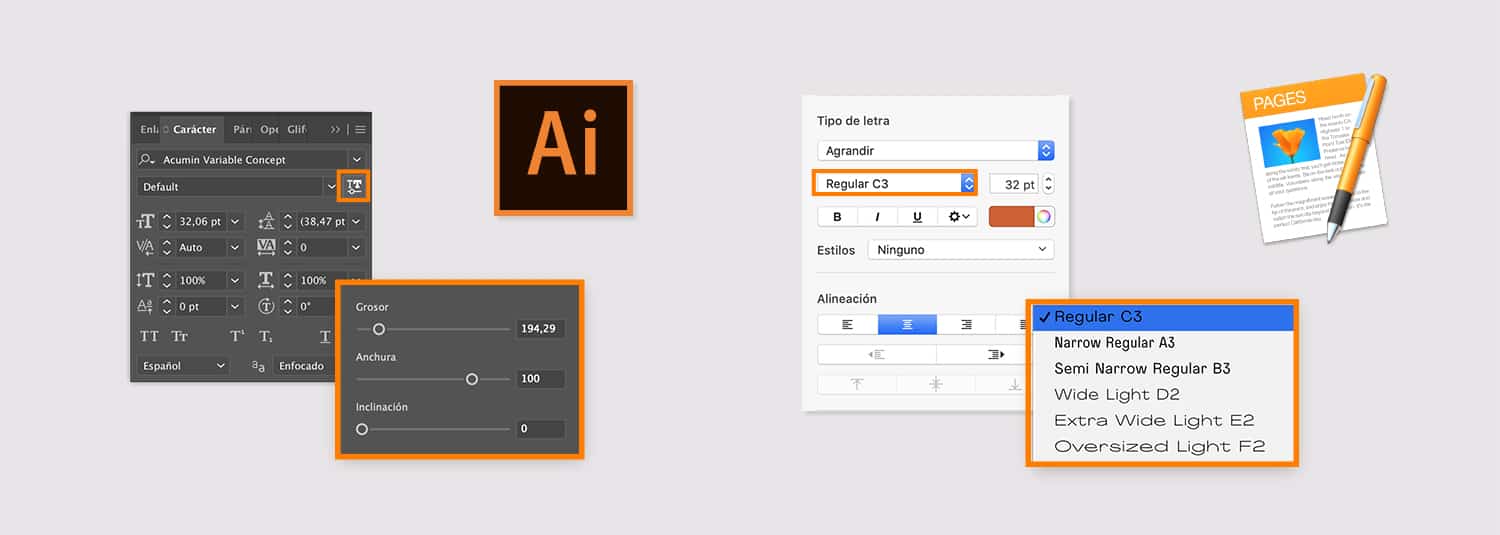
El futuro de las fuentes variables
Las fuentes variables han ganado popularidad en los últimos años debido a su flexibilidad y eficiencia desde su lanzamiento en 2016. Sus capacidades dinámicas son un recurso expresivo valioso para una amplia variedad de proyectos. Este artículo explica las claves del funcionamiento de las fuentes variables y cómo pueden transformar el diseño tipográfico moderno.
Indagamos en las posibilidades de esta nueva tecnología y descubrimos que se abre una emocionante nueva dimensión para el futuro de la tipografía y su integración en sus diferentes medios.
1. QUÉ SON LAS FUENTES VARIABLES
En una fuente variable las formas de las letras (su contorno) van mutando entre mínimo dos estilos (o polos) de una misma tipografía. Este espacio entre dos polos es denominado eje de interpolación. El eje más habitual es el que varía el grosor de la letra. En ese caso, tendremos a un extremo un peso muy fino y en el otro, uno muy grueso. Las fuentes variables permiten interpolar entre estos dos grosores opuestos y elegir cualquier estilo intermedio sin la necesidad de limitarse a uno de los pesos predefinidos (Light, Semibold, Bold etc.).
Ejemplos de la web Variable Fonts: 1. Fuente Ohno Blazeface Variable de James T. Edmondson (OH no Type Co.) – 2. Fuente Cheee Variable de James T. Edmondson (OH no Type Co.) – 3. Fuente Roche Color de Henrique Beier (Harbor Type)
Es posible añadir multitud de ejes de interpolación. En el ejemplo anterior, podría ser el ancho de la letra. La variación se encontraría, entonces, entre un estilo muy estrecho y uno muy ancho. Los ejes predefinidos en la especificación OpenType son peso, ancho, cursiva, inclinación y tamaño óptico. Pero cualquier eje que un tipógrafo decida diseñar es posible.
2. FUENTES VARIABLES Y LA WEB
Resumiendo, podemos decir que una fuente variable es un único archivo de fuente con una inmensa cantidad de posibles estilos de una misma tipografía. Una de las cosas más interesantes de las fuentes variables reside precisamente aquí: en la reducción de múltiples archivos en uno solo y, por lo tanto, en la reducción de su tamaño. Traducido a la funcionalidad web, quiere decir que por fin podemos trabajar con una variedad de estilos casi ilimitados sin que esto afecte al tiempo de carga. El tamaño de los archivos de fuentes que siempre había supuesto una limitación en el entorno web ¡por fin ya dejó de ser un problema! (gracias a las fuentes variables).
Laurence Penney, un interesante agente del mundo tipográfico, a medio camino entre desarrollador de software, diseñador tipográfico y puente entre estos y los usuarios finales y además creador de Axis Praxis (herramienta creada para experimentar y probar fuentes variables y de donde hemos sacado muchos ejemplos para este artículo), lo dice con estas palabras :
«Esta vez será la web que lidere el camino en tipografía, y no las aplicaciones de escritorio. Los diseñadores de UX y los desarrolladores front-end son la nueva vanguardia de la tipografía. Los navegadores están listos o casi listos, el CSS para controlarlos funciona bien, los desarrolladores front-end están ansiosos por jugar, los obsesivos en el ancho de banda serán seducidos por el tamaño reducido. El Desktop se pondrá al día.»
1. Fuente Zycon de David Berlow (Font Bureau) – 2. “Muybridge galloping horse” por Laurence Penney: animación del emoji  ???? U+1F40E – 3. fuente variable de color Mr. Poo por Roel Nieskens (Pixel Ambacht)
Es interesante mencionar que la reducción de tamaño que permiten las fuentes variables, las hace también interesante fuera del mundo de la tipografía para crear pequeñas animaciones y sustituir el formato SVG. Como menciona Laurence Penney en la entrevistas  hecha por Slanted Publishers sobre fuentes variables, podemos imaginar una fuente variable ideada para un set de emojis que cuente con las caras de los “smilies” y donde sean los ojos y boca los que puedan ir mutando.
3. CÓMO SE USAN LAS FUENTES VARIABLES
Puesto que Adobe, Microsoft y Apple han sido los impulsores junto a Google de las fuentes variables, es posible utilizarlas en (algunas de) sus aplicaciones de escritorio.
En Adobe Illustrator y Photoshop (sin embargo, aún no InDesign) los ejes se visualizan en un slider. En él, el usuario puede deslizar el manejador a cualquier punto intermedio entre un extremo y otro. Se visualizarán tantos sliders como ejes tenga definida la tipo.
Programas de escritorio como Apple Page o Microsoft Office, no disponen de estos sliders. Para estos casos, los diseñadores de las fuentes variables pueden definir instancias. Estas instancias equivalen a los estilos de fuente que ya conocemos de antes y se muestran de forma habitual en un menú desplegable (como Extrabold Italic, Condensed Light etc.)
El hecho que los mencionados cuatro gigantes de la tecnología hayan sumado fuerzas para hacer posible las fuentes variables, significó que rápidamente se hizo viable la implementación en todos sus navegadores. Mediante la propiedad CSS “font-variation-settings” es posible controlar la posición de un eje de interpolación (indicado por su código de 4 letras) de una fuente variable.
¿Y tú, qué conceptos imaginas trasladar a fuentes variables? Esto es solo el inicio de un mundo de posibilidades por descubrir. Diseñadores, tipógrafos y programadores tenemos por delante un emocionante futuro tipográfico por explorar conjuntamente.